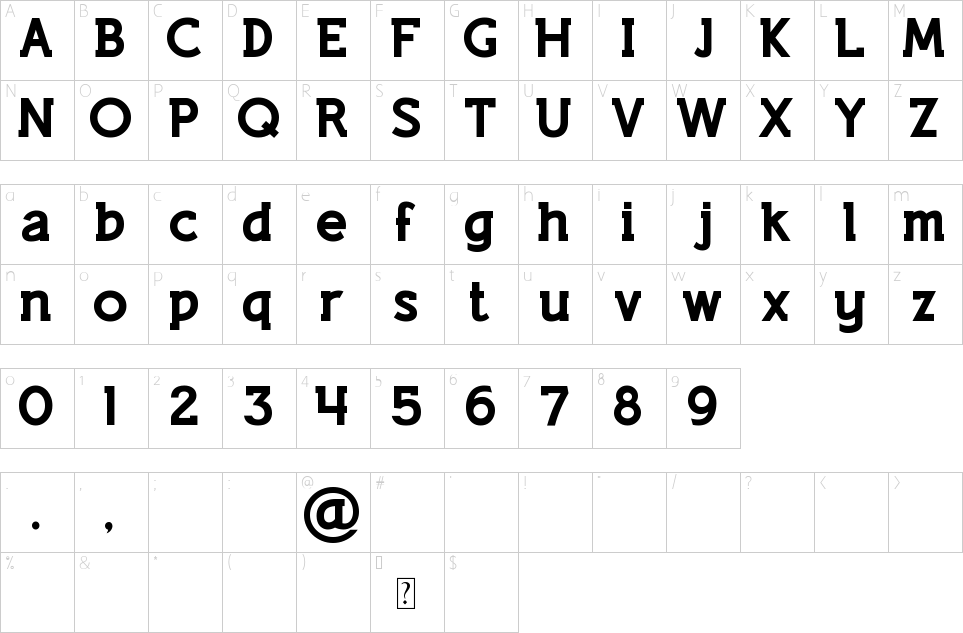
Lifestyle M54 Font – Download Grátis
A Lifestyle M54 é uma elegante e moderna fonte gratuita, perfeitamente adequada para qualquer projeto de design que busca um equilíbrio entre beleza e funcionalidade. Ela foi projetada por justme54s, um nome não informado na descrição original, mas isso apenas reforça seu status como um designer criativo desconhecido, ainda assim talentoso. Essa font é ideal para criar designs que valorizem a simplicidade e o bom gosto. Com mais de quatro mil downloads, essa font tem provado ser bastante valorizada pela comunidade do design gráfico, se tornando uma opção popular entre designers que buscam um acabamento sofisticado em seus projetos digitais. Se você está procurando por uma fonte gratuita e de alta qualidade para seu próximo projeto, a Lifestyle M54 pode ser justamente o que você precisa, oferecendo tanto estilo quanto facilidade de uso.